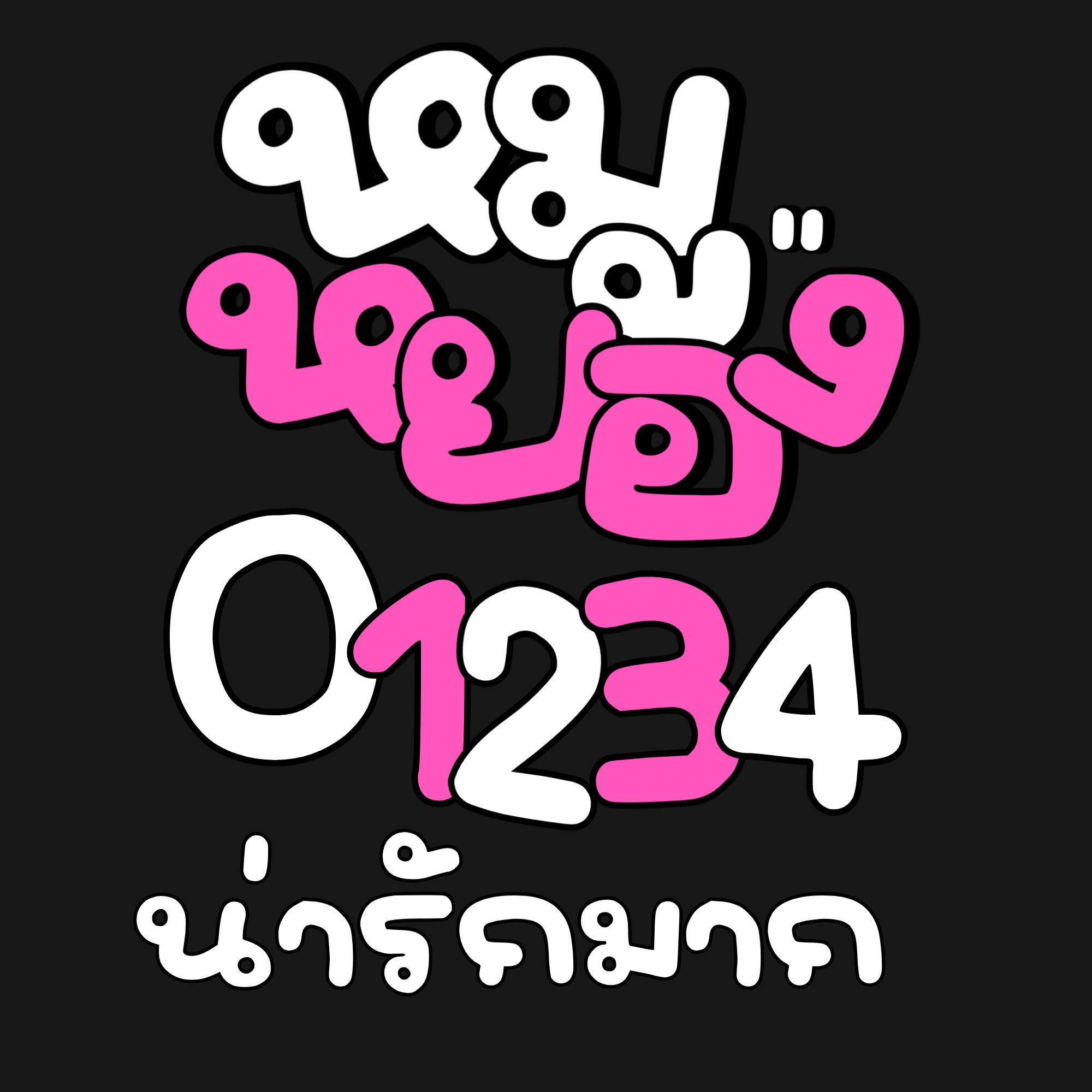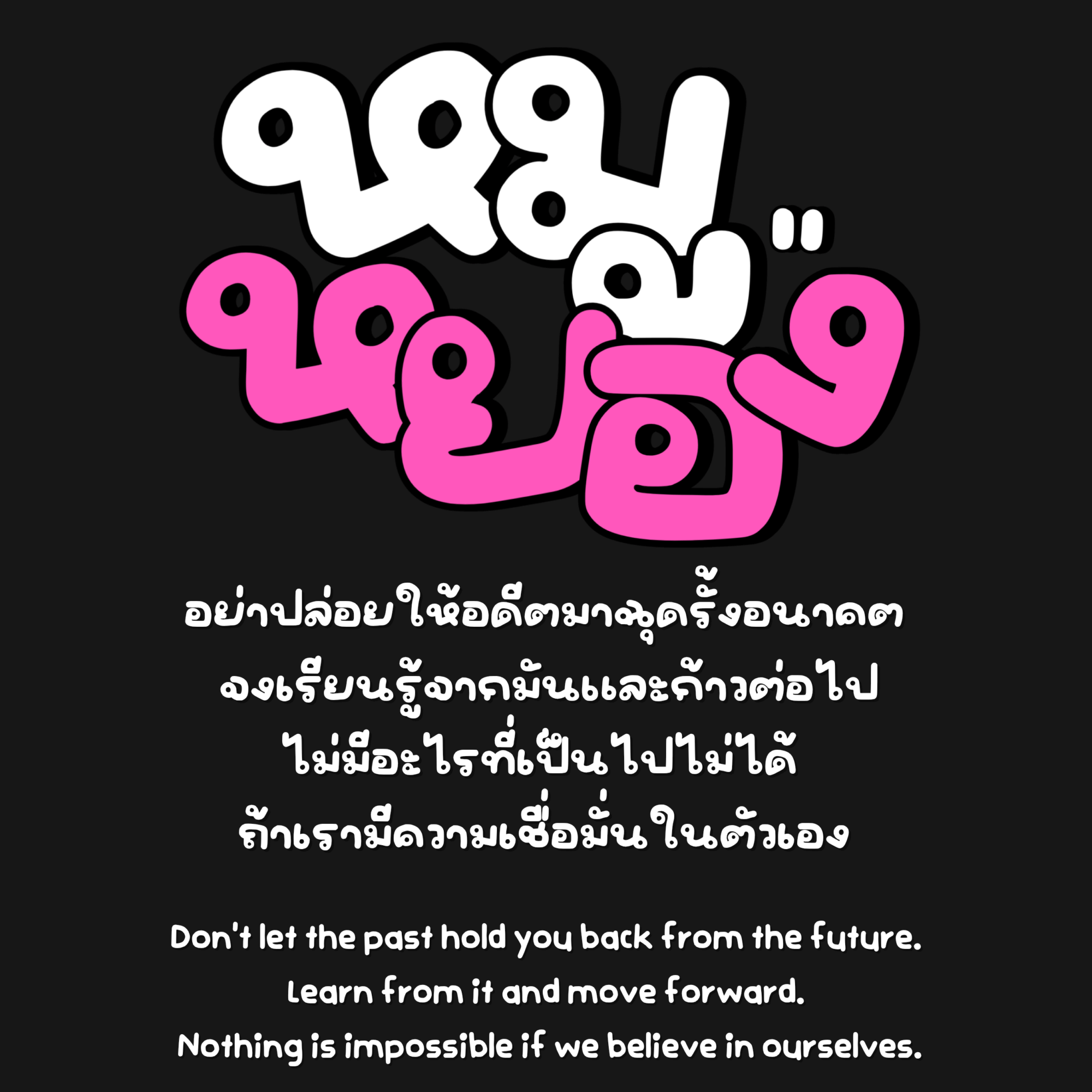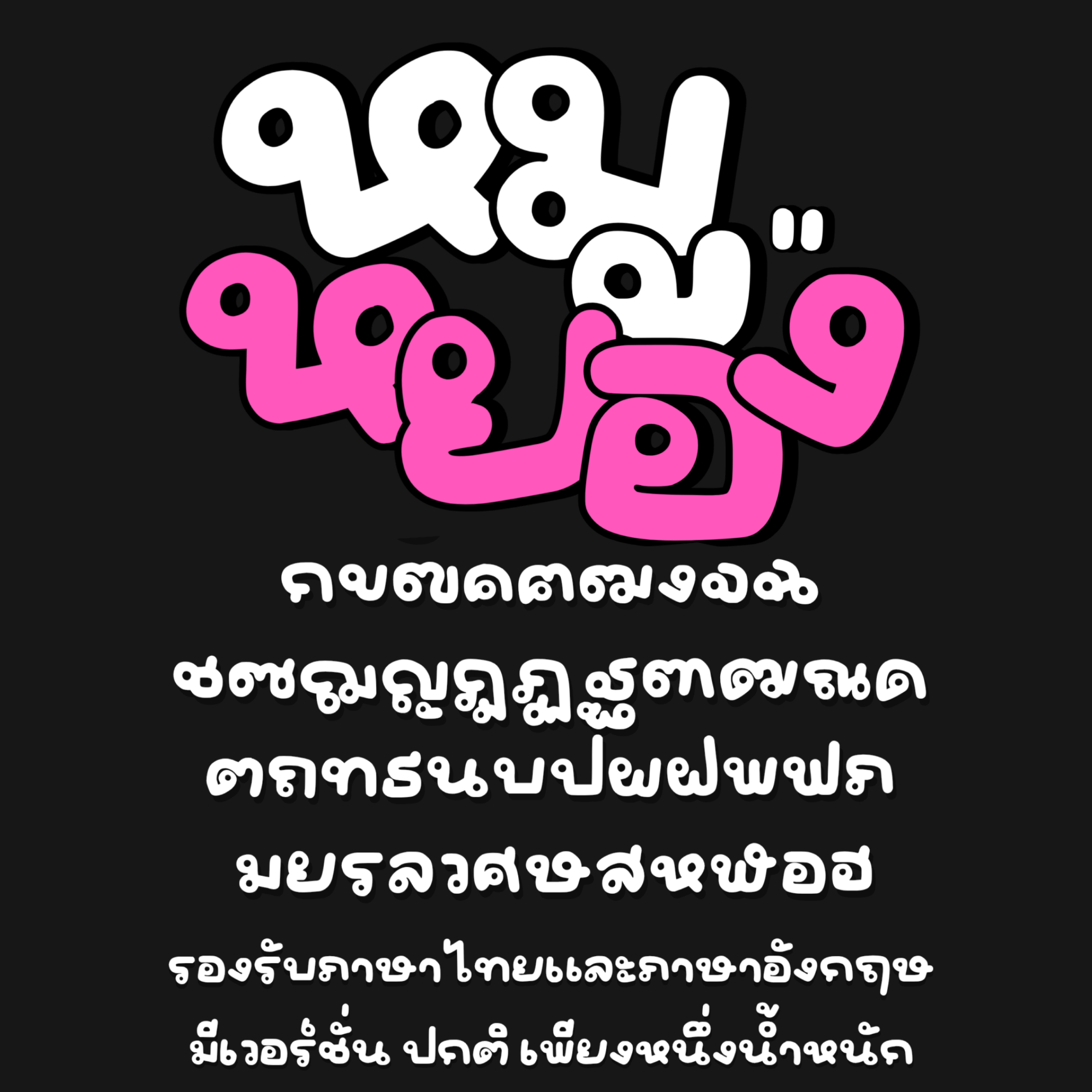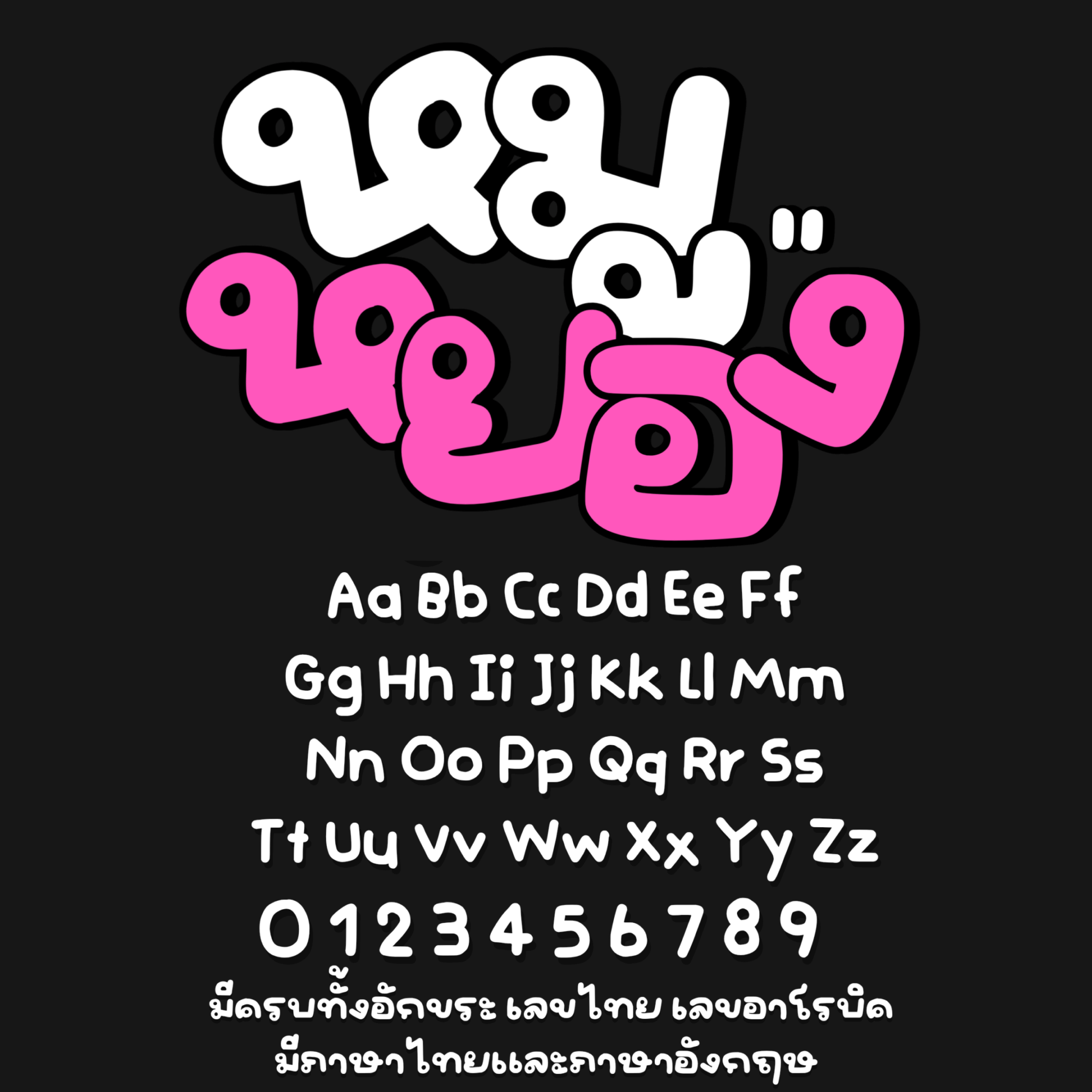
แจกตัว Demo เพื่อทดลองใช้งานฟรี อิมหมูหยองฟอนต์ – ตัวอ้วนหนาเหมาะกับทุกสายงานเลยย
เหมาะกับทุกสายครีเอเตอร์ ไม่ว่าจะใช้ทำป้าย ข้อความ โพสต์ หรือคอนเทนต์น่ารักๆ
IMTYC อิมหมูหยอง